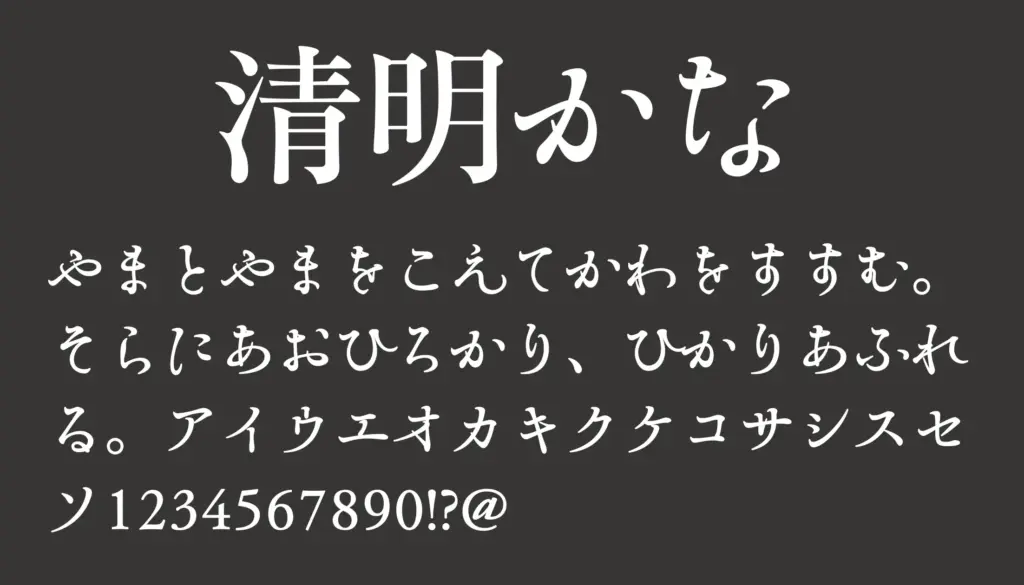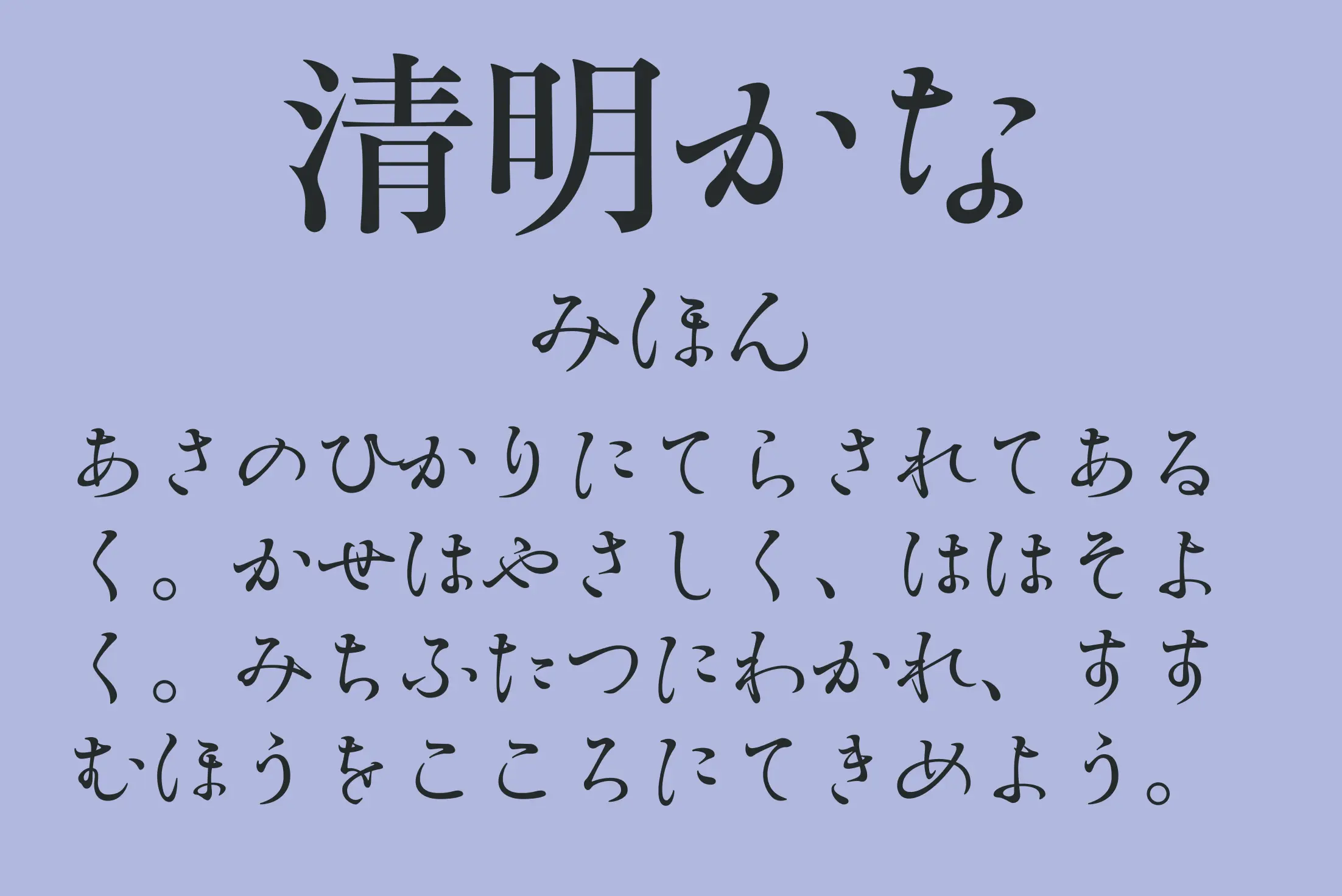
伸びやかな線と凛とした美しさを両立。名前どおり「清々しい明朝」の趣があり、躍動感と訴求力を兼ね備えています。短めの見出しやキャッチコピー、紙やWebのクリエイティブ作品に向いており、オールド感と現代の整った組版に対応するマルチ性が魅力です。
清明かな
| 収録文字 | ひらがな(濁音・半濁音は未収録)・カタカナ(濁音・半濁音は未収録)・数字・記号 |